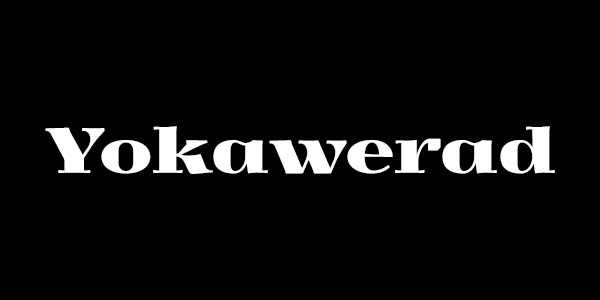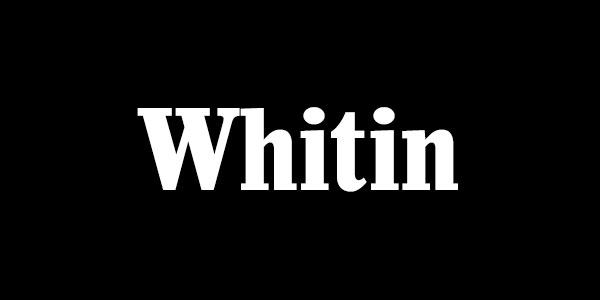
10 Serif Bold Font Terbaik Untuk Typography dan Headings
Salah satu bagian terpenting dari sebuah artikel selain isi artikel tersebut adalah Heading, walau artikel yang ditulis bagus dan menarik namun jika heading artikel tersebut tidak disusun atau di tata dengan benar maka akan mengurangi daya tarik serta minat orang untuk membacanya, dan sebaliknya jika heading-nya di buat dengan font dan kalimat yang lebih baik maka otomatis orang akan lebih penasaran dan ingin membaca artikel tersebut.
Penulisan dan tata bahasa yang baik menjadi cara yang ampuh untuk membuat heading yang baik, tapi jika hal tersebut tidak dibarengi dengan pemilihan jenis huruf/font yang tepat maka hasil yang didapat tidaklah maksimal. Berikut adalah beberapa font rekomendasi terbaik pilihan Author yang cocok untuk dipakai sebagai tipografi dan heading artikel, diambil dari beberagai sumber dan telah di coba beberapa diantaranya :
Free Abril FatFace Bold Serif Font
Free Bambi Bold Serif Font
Free Bodoni Bold Serif Font
Free Colus Bold Serif Font
Free John Hancock CP Bold Serif Font
Free Mermaid Bold Serif Font
Free Otama e.p Bold Serif Font
Free Sling Bold Serif Font
Free Spinwerad Bold Serif Font
Free Whitin Bold Serif Font
Free Yokawerad Bold Serif Font